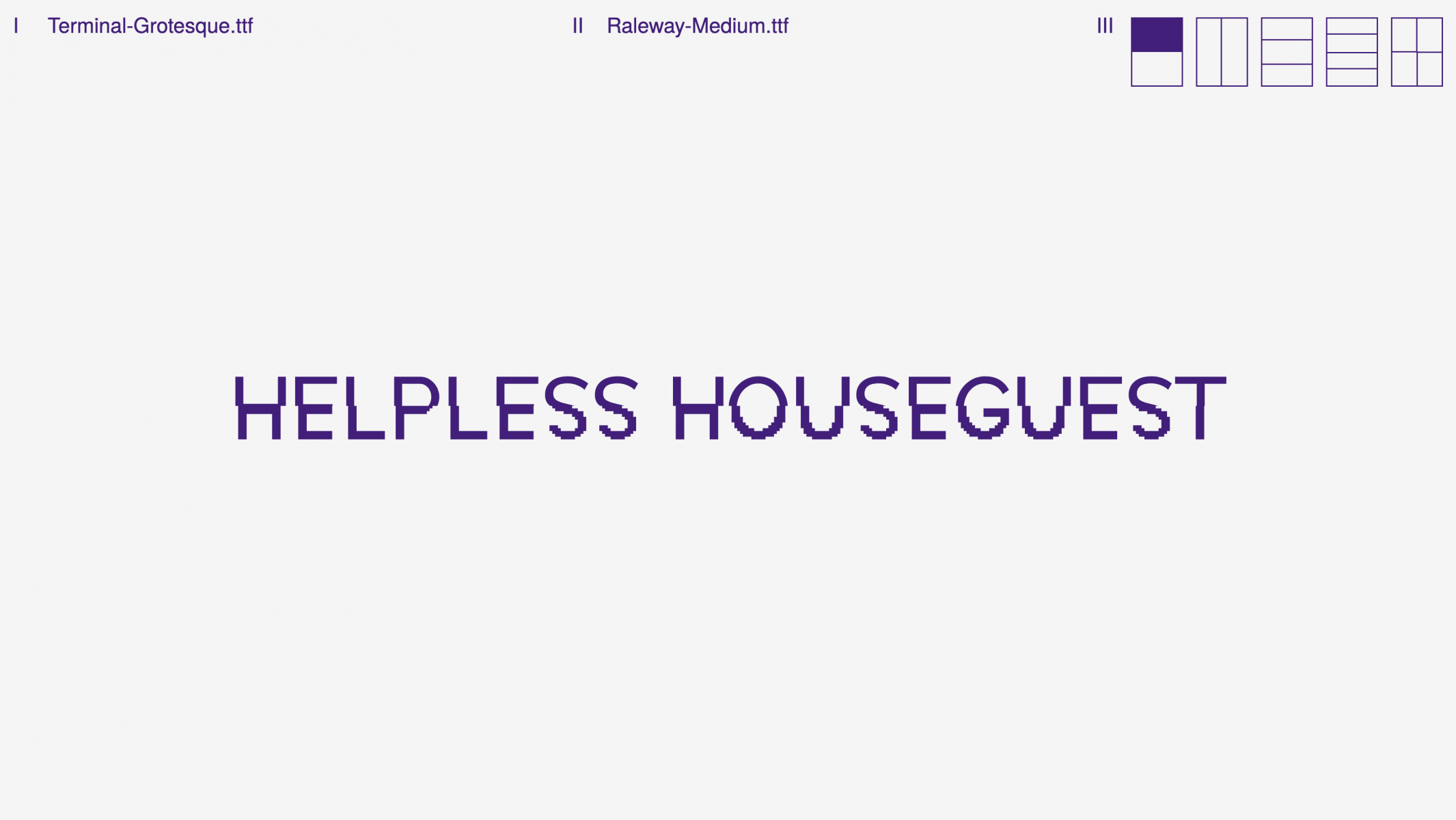
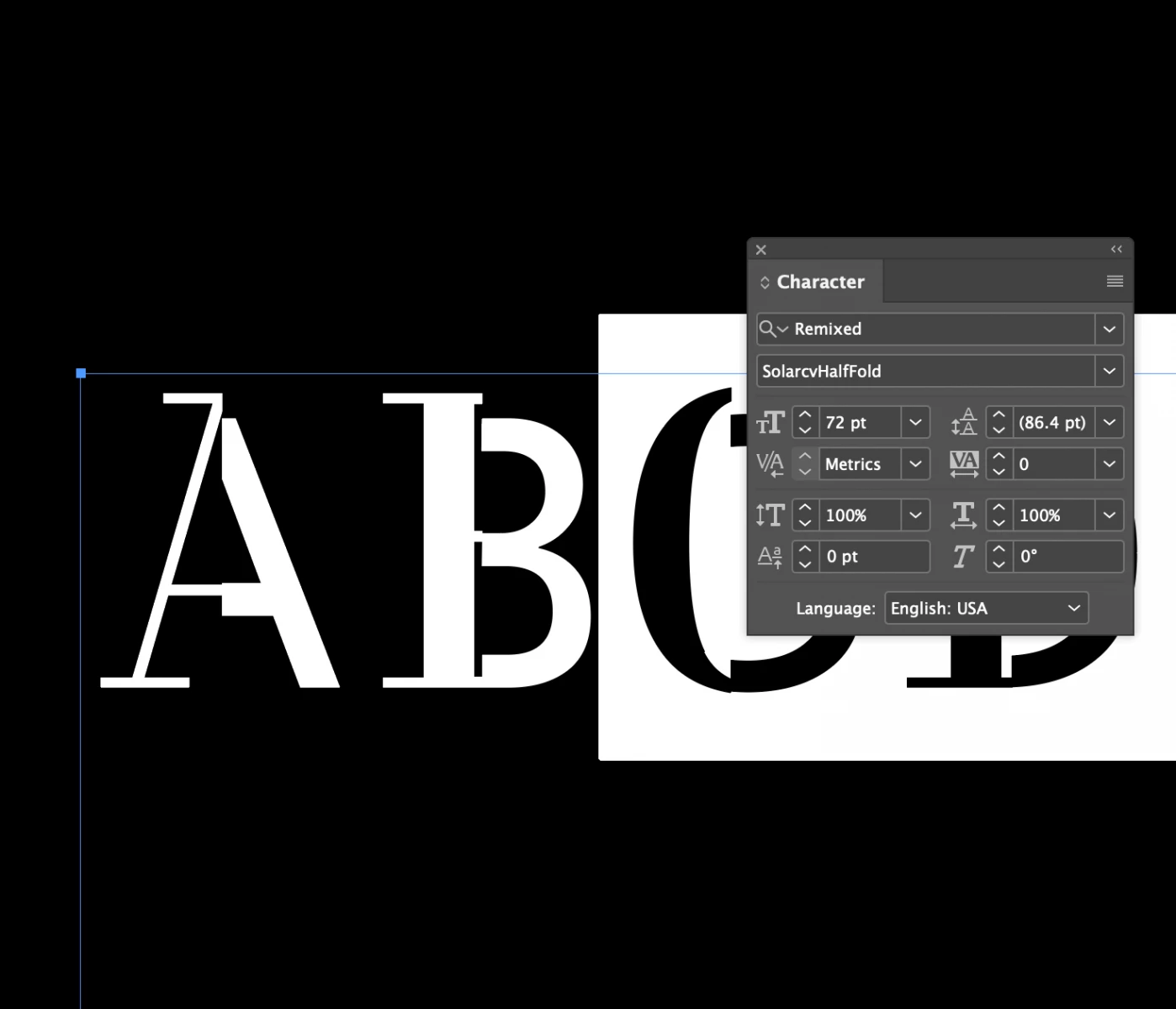
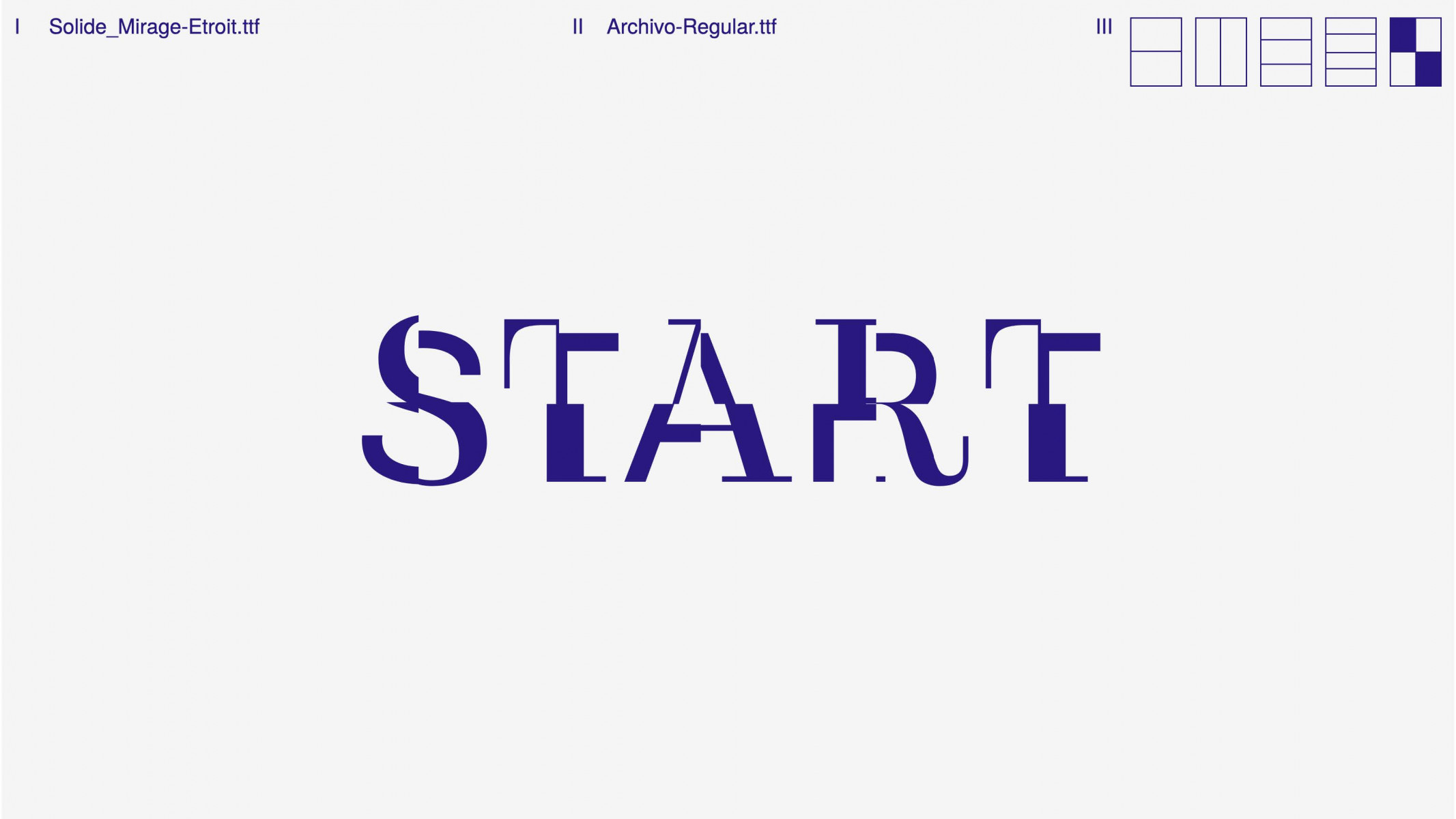
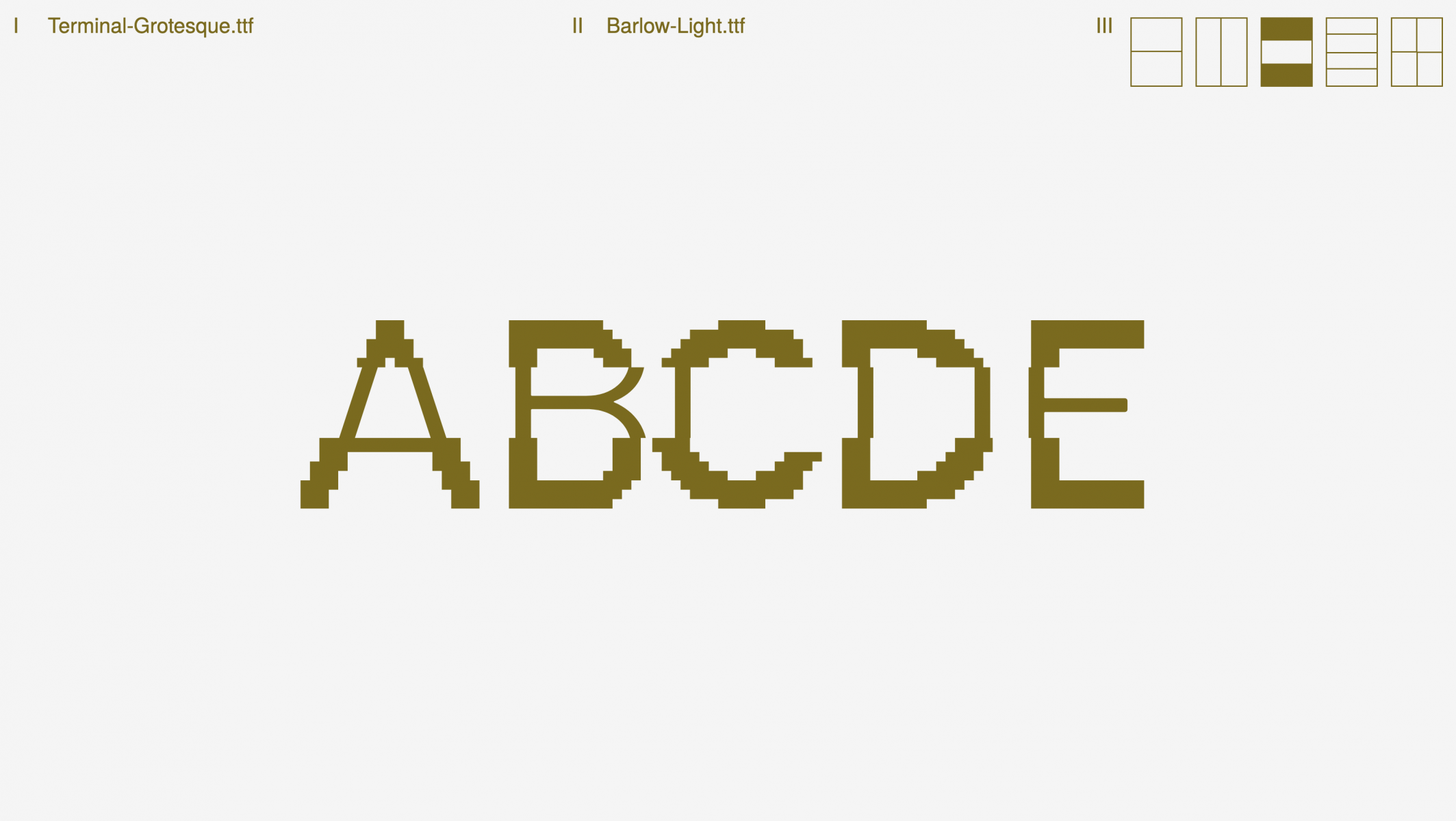
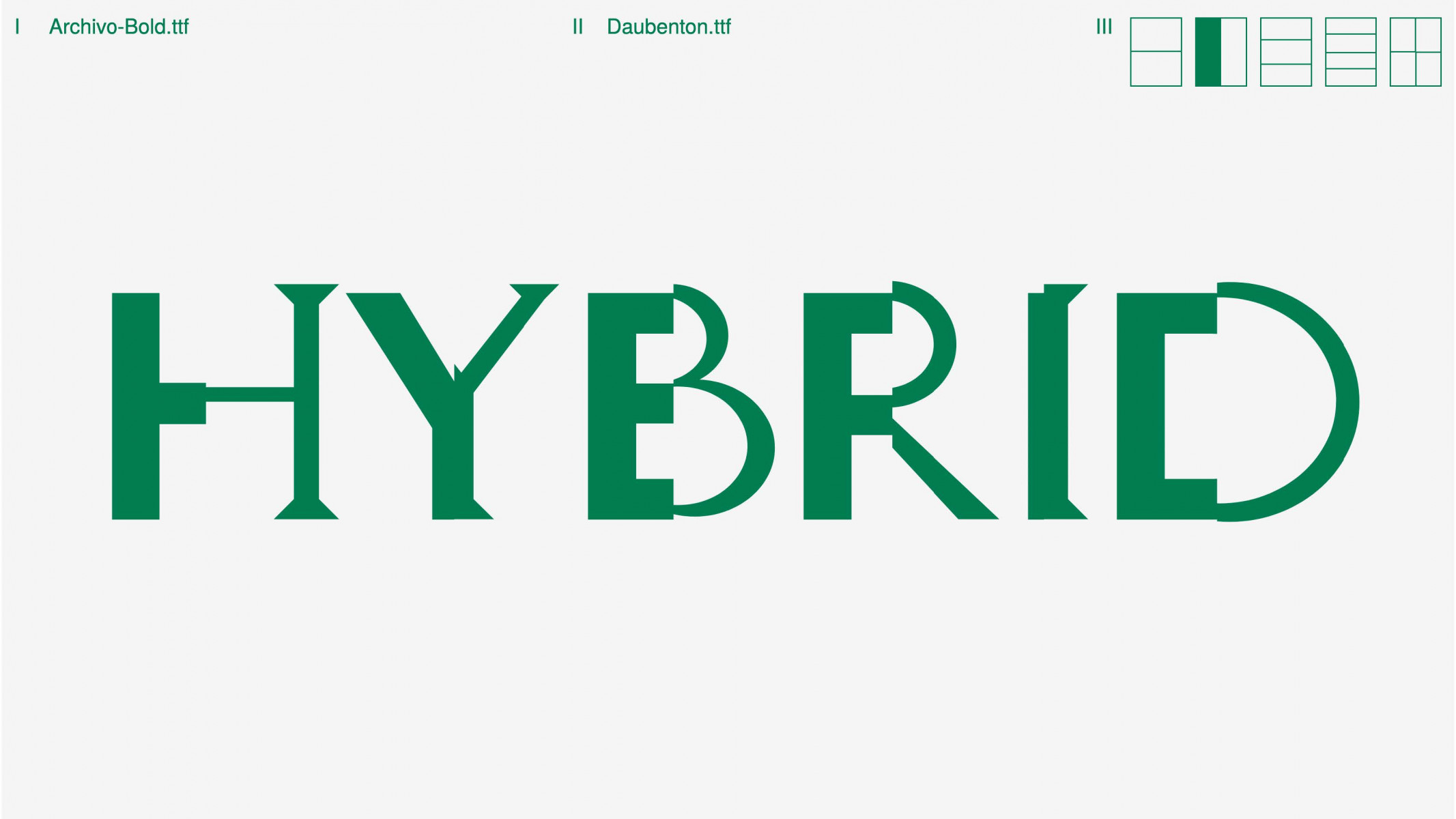
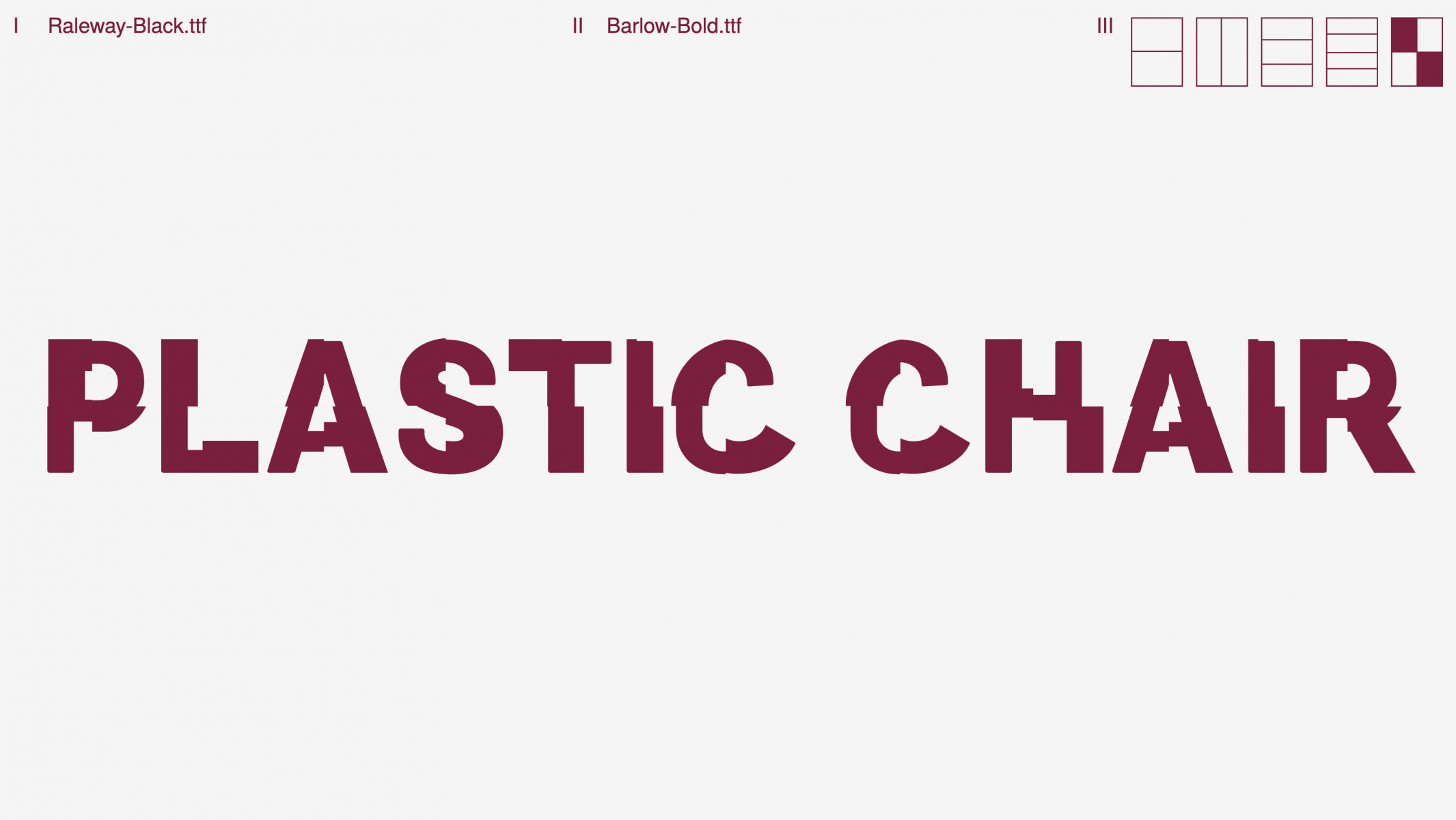
Relevancia
Bigdot es una herramienta que explora la generación tipográfica a través de la combinación algorítmica de fuentes existentes, ofreciendo una nueva forma de interacción para el diseño tipográfico.
Su principal aportación reside en que el usuario no diseña desde cero, sino que actúa como un remezclador, seleccionando como ingredientes las tipografías que el sistema combina para crear un resultado nuevo.
La relevancia de este proyecto es que demuestra el potencial del código para expandir las posibilidades del diseño tipográfico, convirtiendo la creación de fuentes en un proceso colaborativo entre el diseñador de la herramienta y el usuario final.